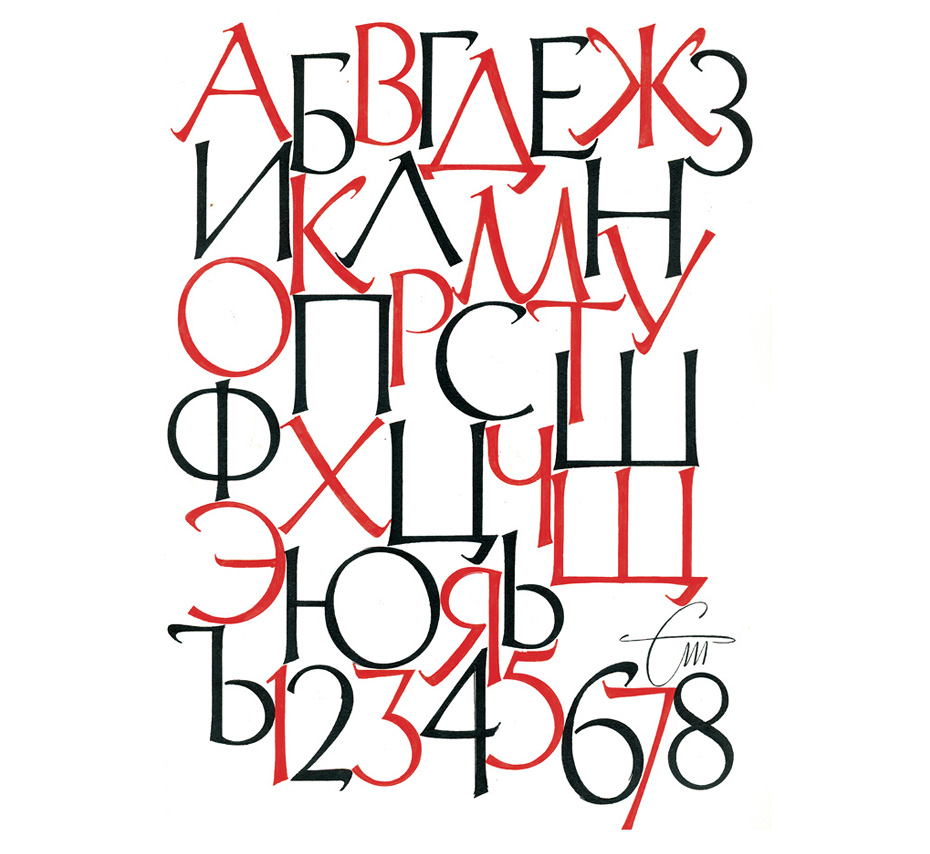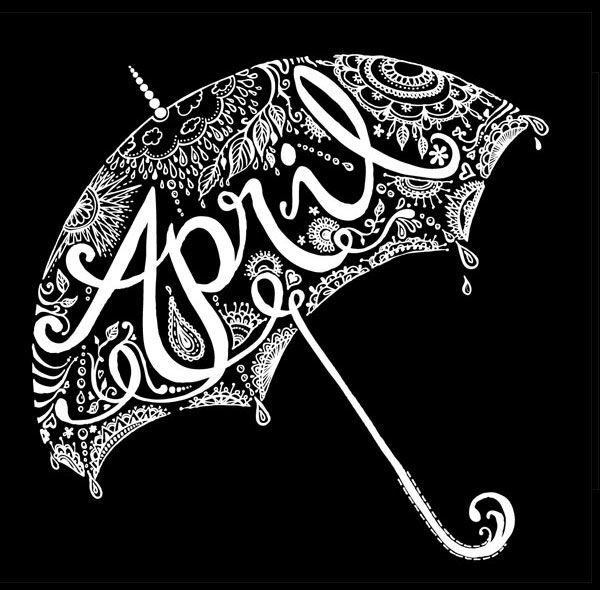
Искусство шрифта
Цель урока: формирование умения использовать приемы, средства композиции, развитие эстетического вкуса на примере художественных произведений, построенных с учетом композиционных законов.Задачи урока:
образовательная: знакомство с художественным оформлением печатной продукции; определение характера шрифта, введение в композицию буквы как изобразительно-смыслового символа;
развивающая: дальнейшее формирование коммуникативных навыков; развитие познавательного интереса через многообразие полиграфической продукции;
воспитательная: воспитание культуры изобразительной деятельности; формирования умения критично относиться к собственной работе и к работе товарищей.
II. Объяснение нового материала.
Сегодня мы поговорим об искусстве композиции. Искусство композиции лежит в основе Графического Дизайна и определяет облик книг, журналов, плакатов, влияет на их образное восприятие.
Слайд 1. Тема урока «Буква – строка – шрифт. Искусство шрифта».
Слайд 2.
Дизайн – англ. «designe» – замысел, умысел, план, цель, намерение, творческий замысел, проект, чертеж, расчет, конструкция; эскиз, рисунок, узор, композиция искусство композиции, произведение искусства.
Дизайн – это творческий метод, процесс и результат художественно-технического проектирования промышленных изделий, их комплексов и систем, ориентированный на достижение наиболее полного соответствия создаваемых объектов и среды в целом возможностям и потребностям человека, как утилитарным, так и эстетическим
Слайд 3.
Какие основные категории и принципы в дизайне Вы можете назвать?
Ответы детей: цвет, форма – основные категории и единство, баланс, контраст – основные принципы дизайна.
Слайд 4.
Компьютерные технологии всё глубже проникают во все сферы человеческой деятельности. Художники и дизайнеры в своём творчестве активно и плодотворно используют возможности программно-технических комплексов на базе персональных компьютеров. В полиграфическом и промышленном дизайне творческие работы в настоящее время практически повсеместно создаются при помощи компьютерных технологий.
Компьютерный дизайн мы можем определить, как область дизайна, в которой в качестве основного инструмента художественного конструирования и проектирования используется компьютер.
Ключевым понятием, определяющим особенность этого вида художественного творчества в словосочетании «компьютерный дизайн» является понятие «дизайн». С возникновением и развитием компьютерной графики, художники-дизайнеры одними из первых начали её использовать в своём творчестве, и компьютерный дизайн в настоящее время применяется практически во всех областях дизайна:
– собственно графику;
– полиграфический дизайн;
– электронные издания;
– Web– дизайн;
– трехмерную графику
Слайд 5.
На предыдущих занятиях мы выяснили как воздействую на наше восприятие различные свободные формы – пятна и линии. Такие композиции воздействуют только ассоциативно-образно и никакой конкретной информации не несут. Но есть композиции, состоящие из линий, которые имеют конкретный смысл – это буквы.
Слайд 6.
Любая буква или иероглиф прежде всего изображение. Буква ведет свою родословную от рисунка. В глубокой древности всю информацию обозначали рисунками. Картинное, или рисуночное письмо в виде наскальных рисунков у первобытных людей – называется пиктограммой.
Слайд 7.
Потом рисунки превратились в первые буквенные символы, которые и стали основой написания современных букв. (Рассматриваем рисунок.)
Слайд 8.
На смену пиктографическому письму пришло и деографическое. Предметы изображались либо символическими знаками (солнце, луна), либо графическими изображениями: птица, зверь и т.д.
Слайд 9.
Буквенно-звуковое письмо появилось во втором тысячелетии до н.э. В нем знаки означали отдельные звуки (фонемы). Причем знаки в зависимости от произношения могли по-разному передавать звуковые особенности языка. В буквенно-звуковом письме с помощью графических знаков можно было передавать человеческую речь
Слайд 10.
С течением времени графические знаки усовершенствовались, на смену одним приходили другие, более простые по форме, передающие новое значение.
Слайд 11.
Шрифт (или шрифтовая гарнитура) – это буквы, объединенные одним стилем графического начертания.
Сравните шрифты , придуманные разными дизайнерами.
Под рукой художника-дизайнера буквы приобретают форму и пропорции, свойственные только данному шрифту. От того, каким шрифтом, каким кеглем (т.е. размером шрифта) написано слово, зависит и его восприятие. На нас воздействует не только смысл слова, но и характер шрифта.